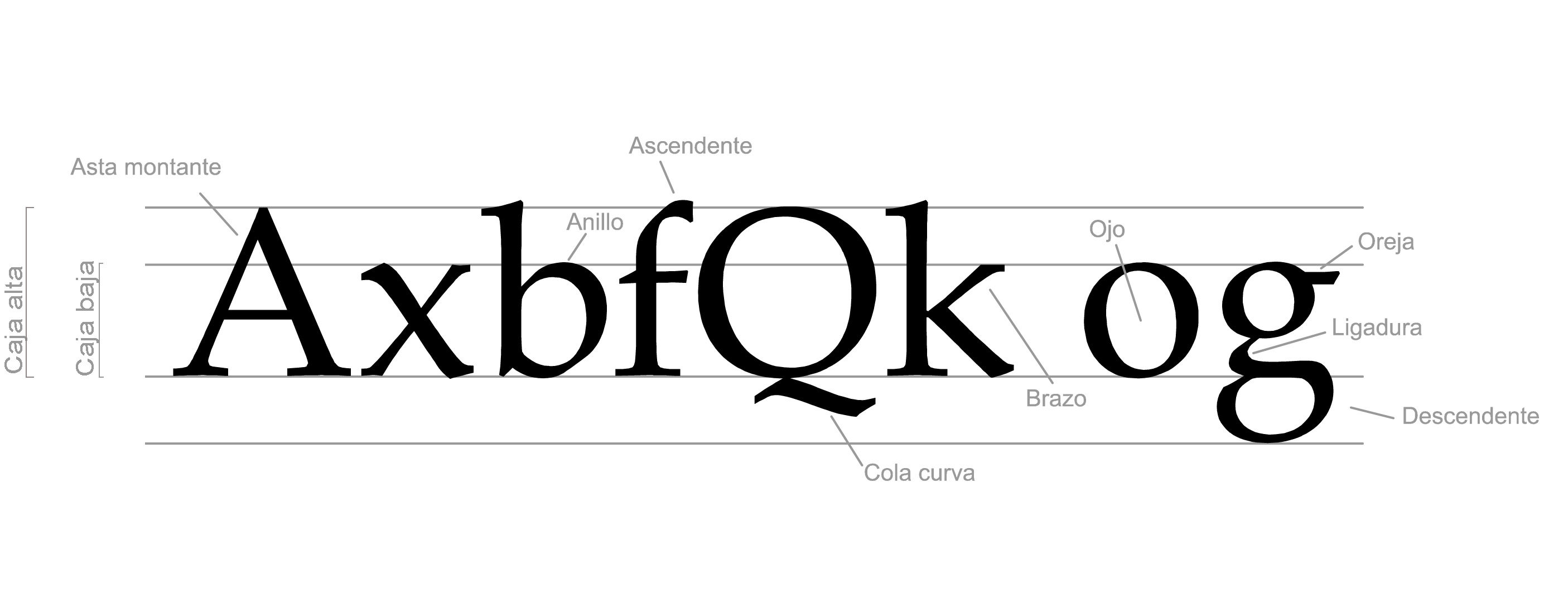
Tipografía del diseño
Es el arte de diseñar letras y componer texto de tal modo que puedan leerse de un modo fácil, eficaz y agradable.
Tipografía del diseño
Arte
Técnica
Selección
Letra
Diseño
Forma
Tipo
Partes
Asta
Asta montantes
Brazo
Cola
Ascendente
Descendente
Línea base
Oreja
Ojo
Anillo
Rebaba
Serif
Elementos
Presencia o ausencia del serif
Forma del serif
Relación curva y recta
Uniformidad o variabilidad
Dirección de eje de engrosamiento
Tipografías Serif
Romanas antiguas
Romanas de transición
Romanas modernas
Egipcias